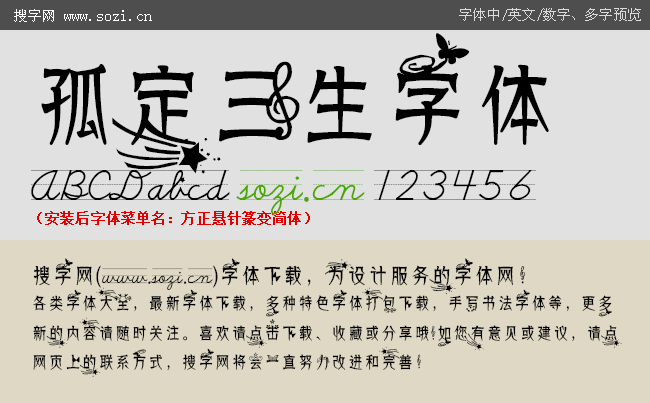
孤定三生字體
搜字網(wǎng)給大家提供一款孤定三生字體手機(jī)中文字體下載。這款手機(jī)字體是在方正懸針篆變簡(jiǎn)體筆畫間插入了漂亮的蝴蝶與音符等卡通圖案。方正懸針篆變字體意在保留篆書韻味,同時(shí)將隸書與楷書筆畫特征熔于一爐,端莊秀美、開張疏朗,雍容大氣、復(fù)古卻易讀。加入了卡通圖案后又增添了趣味性,特別適合喜歡手機(jī)字體個(gè)性一些的朋友在手機(jī)上安裝使用。